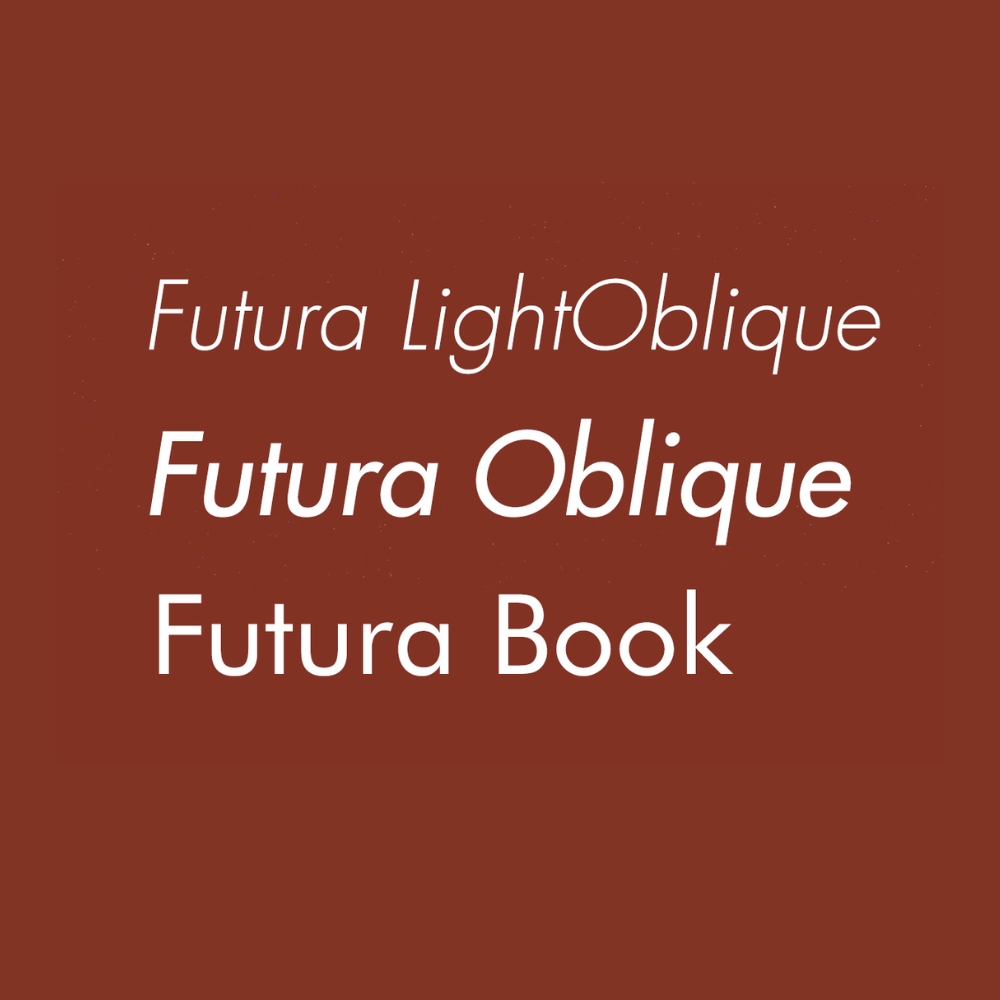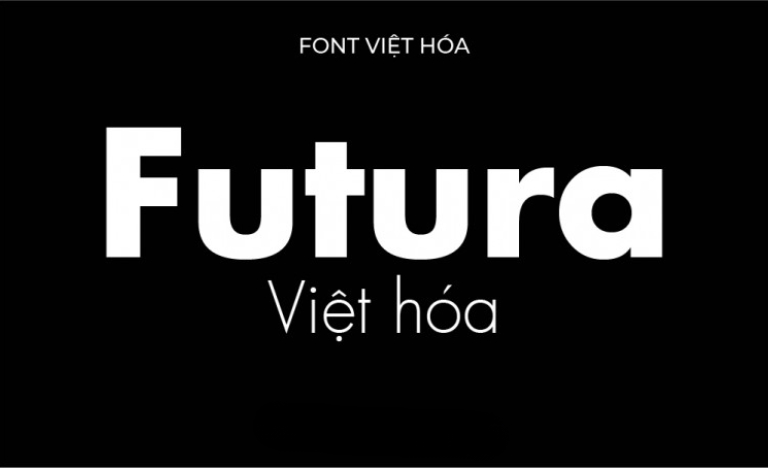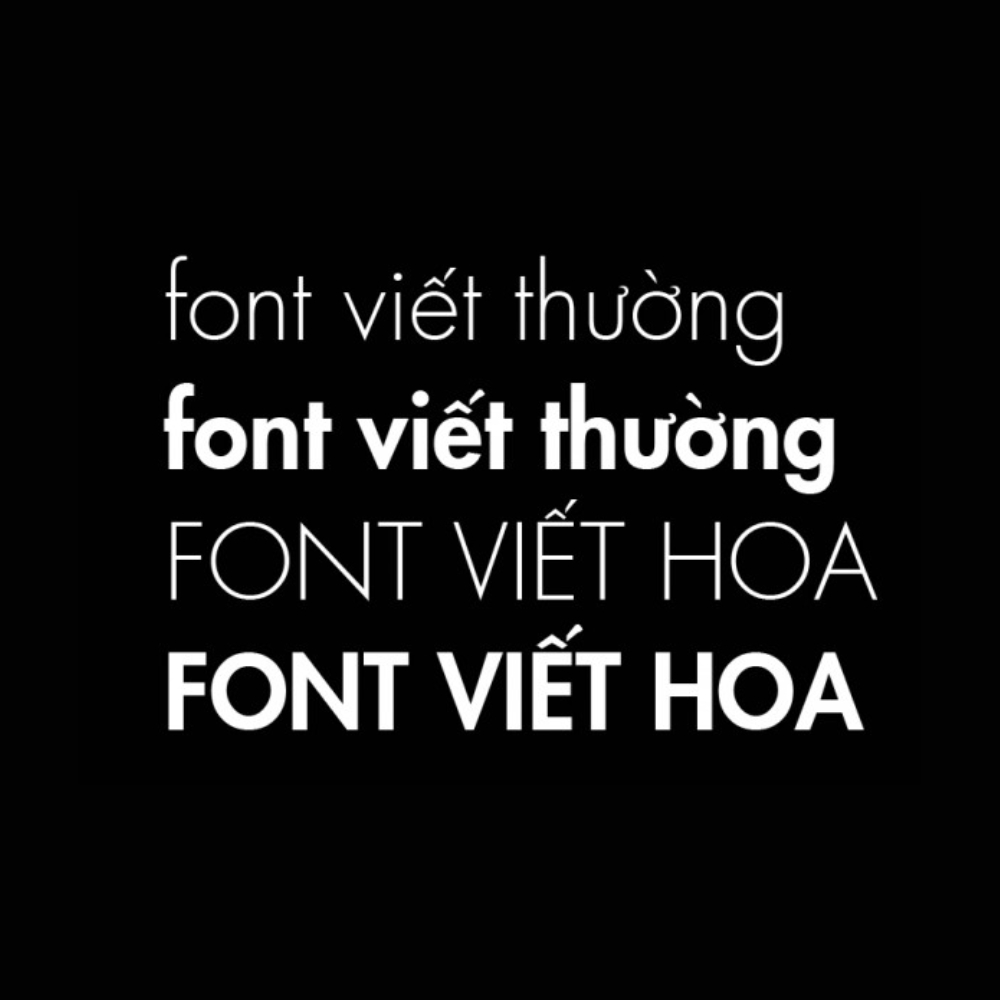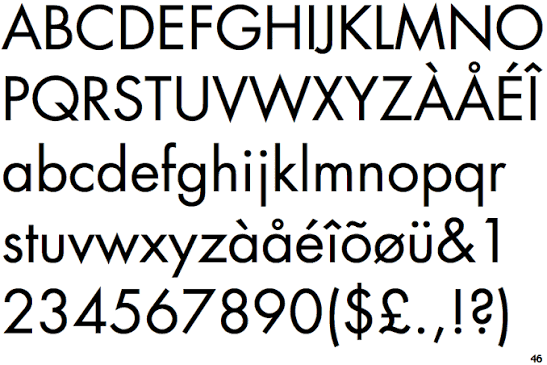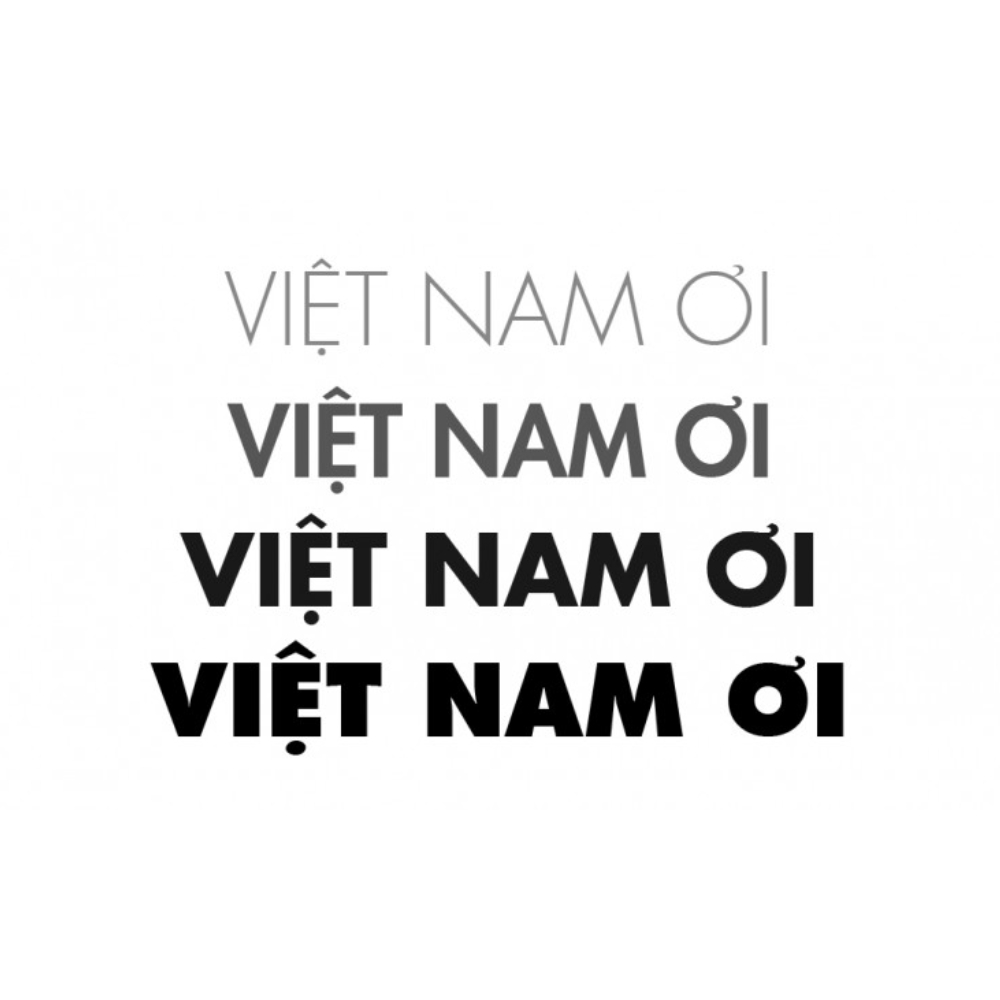
Futura là một trong những bộ font chữ Sans-serif mang tính biểu tượng, được thiết kế bởi Paul Renner vào năm 1927 dựa trên triết lý của trường phái Bauhaus. Với cấu trúc dựa trên các khối hình học cơ bản như hình tròn, hình tam giác và hình vuông, bộ font này mang lại vẻ đẹp hiện đại, sạch sẽ và cực kỳ hiệu quả trong trình bày văn bản.
Sức hút bền vững từ dòng font Futura trong thiết kế hiện đại
Điểm lôi cuốn của dòng font chữ này nằm ở sự tối giản nhưng đầy sức mạnh thị giác. Thay vì sử dụng các chi tiết trang trí rườm rà, Futura tập trung vào sự cân bằng và tính minh bạch của từng ký tự. Bản font Futura Việt hóa đã được xử lý kỹ lưỡng hệ thống dấu thanh tiếng Việt, giúp các nội dung thuyết minh dự án hay ghi chú trên bản vẽ luôn giữ được sự chỉn chu, đồng bộ với tinh thần hiện đại của bộ chữ gốc.
Sự linh hoạt của Futura còn thể hiện qua khả năng ứng dụng đa dạng trên nhiều loại ấn phẩm khác nhau. Dù được sử dụng trên các màn hình kỹ thuật số độ phân giải cao hay in ấn trên các vật liệu thực tế như panel, gỗ, alu, bộ font này vẫn duy trì được độ rõ nét và cảm giác sang trọng. Đây là phương án phù hợp cho những ai muốn truyền tải tư duy thiết kế khoa học, gọn gàng và có tầm nhìn dài hạn cho các công trình xây dựng hiện đại.
Gợi ý trình bày: Font Futura mang tính hình học rất cao nên đôi khi tạo cảm giác hơi cứng. Để bản thiết kế hài hòa hơn, bạn nên phối hợp giữa các độ đậm nhạt khác nhau trong cùng một gia đình font hoặc sử dụng một font Serif thanh mảnh cho phần trích dẫn để tạo điểm nhấn tinh tế.
03 Ứng dụng thực tế của font Futura Bold trong hồ sơ kiến trúc
Nhờ vẻ ngoài vững chãi và sự mạch lạc, font Futura Bold cùng các biến thể khác mang lại giá trị thực tế khi được đưa vào khâu vận hành và quảng bá dự án:
- Hồ sơ năng lực dự án nhà lắp ghép: Sử dụng futura bold font cho các tiêu đề chính giúp thể hiện sự chuyên nghiệp và uy tín của đơn vị thi công ngay từ cái nhìn đầu tiên.
- Ghi chú kỹ thuật trên bản vẽ CAD: Độ rõ nét của Futura giúp các thông số về kích thước vật liệu, kết cấu thép hay chi tiết panel trở nên dễ đọc, hỗ trợ đội ngũ giám sát triển khai công việc hiệu quả tại hiện trường.
- Hệ thống biển hiệu văn phòng container: Các nét chữ hình học của Futura rất ăn ý khi được cắt chữ nổi hoặc in decal trang trí không gian làm việc hiện đại, mang lại sự đồng bộ cho kiến trúc công trình.
03 Lưu ý khi trình bày bố cục chuyên nghiệp với font Futura Việt hóa
- Kiểm soát khoảng cách dòng và chữ: Do cấu trúc chữ Futura có xu hướng chiếm diện tích theo chiều ngang, bạn nên nới rộng khoảng cách dòng một chút để văn bản thông thoáng, giúp người đọc tiếp nhận thông tin dễ dàng hơn.
- Phân cấp thông tin rõ ràng: Hãy sử dụng font Futura Bold cho các đầu mục quan trọng và các kiểu chữ Medium hoặc Book cho phần nội dung chi tiết. Sự tương phản về độ đậm sẽ giúp bố cục hồ sơ thuyết minh dự án trở nên chuyên nghiệp.
- Lựa chọn kích thước hiển thị: Futura hiển thị cực tốt ở kích thước lớn. Với các đoạn văn bản dài ở kích thước nhỏ, bạn nên kiểm tra kỹ độ sắc nét khi in ấn để đảm bảo thông tin không bị dính nét.